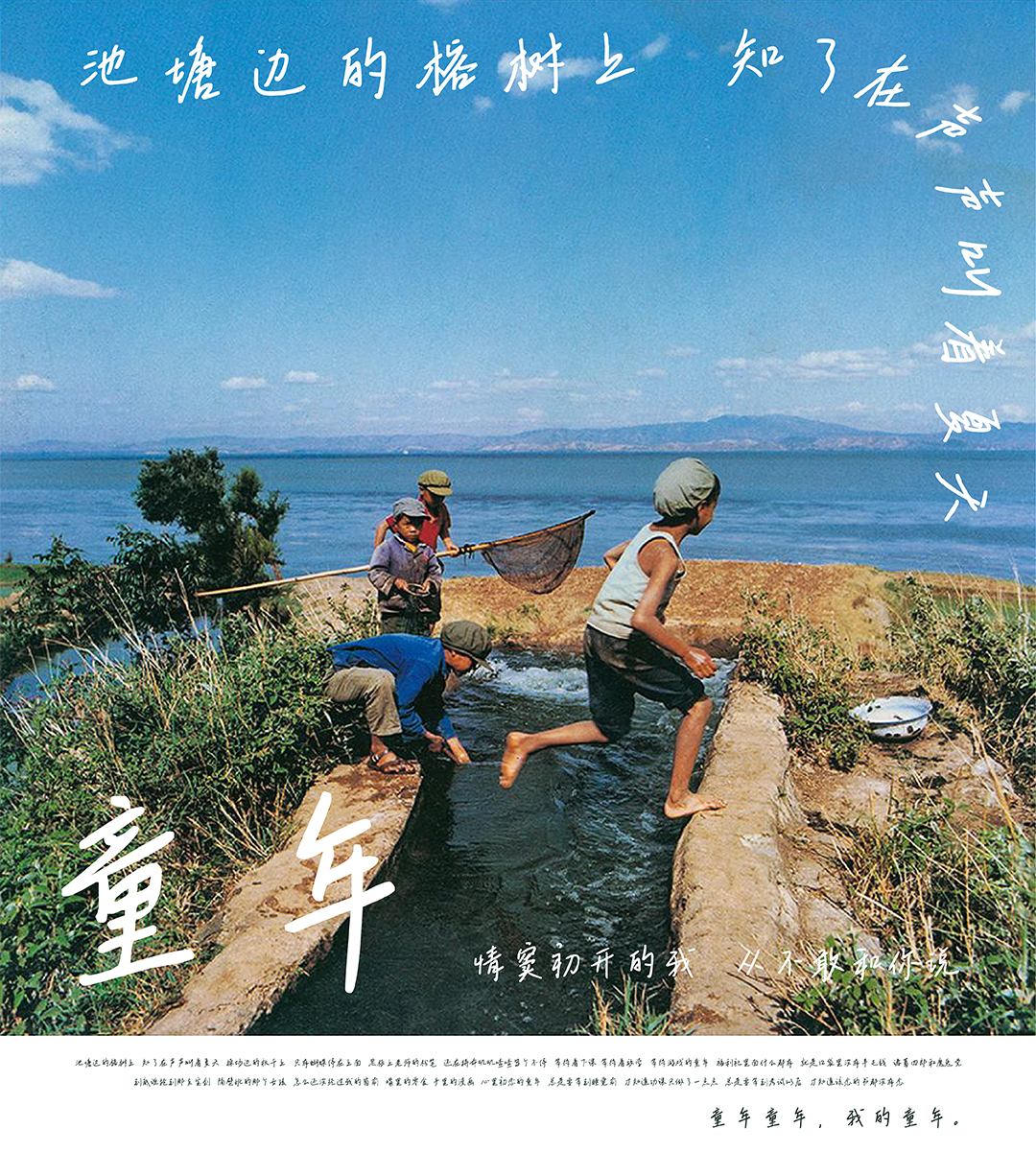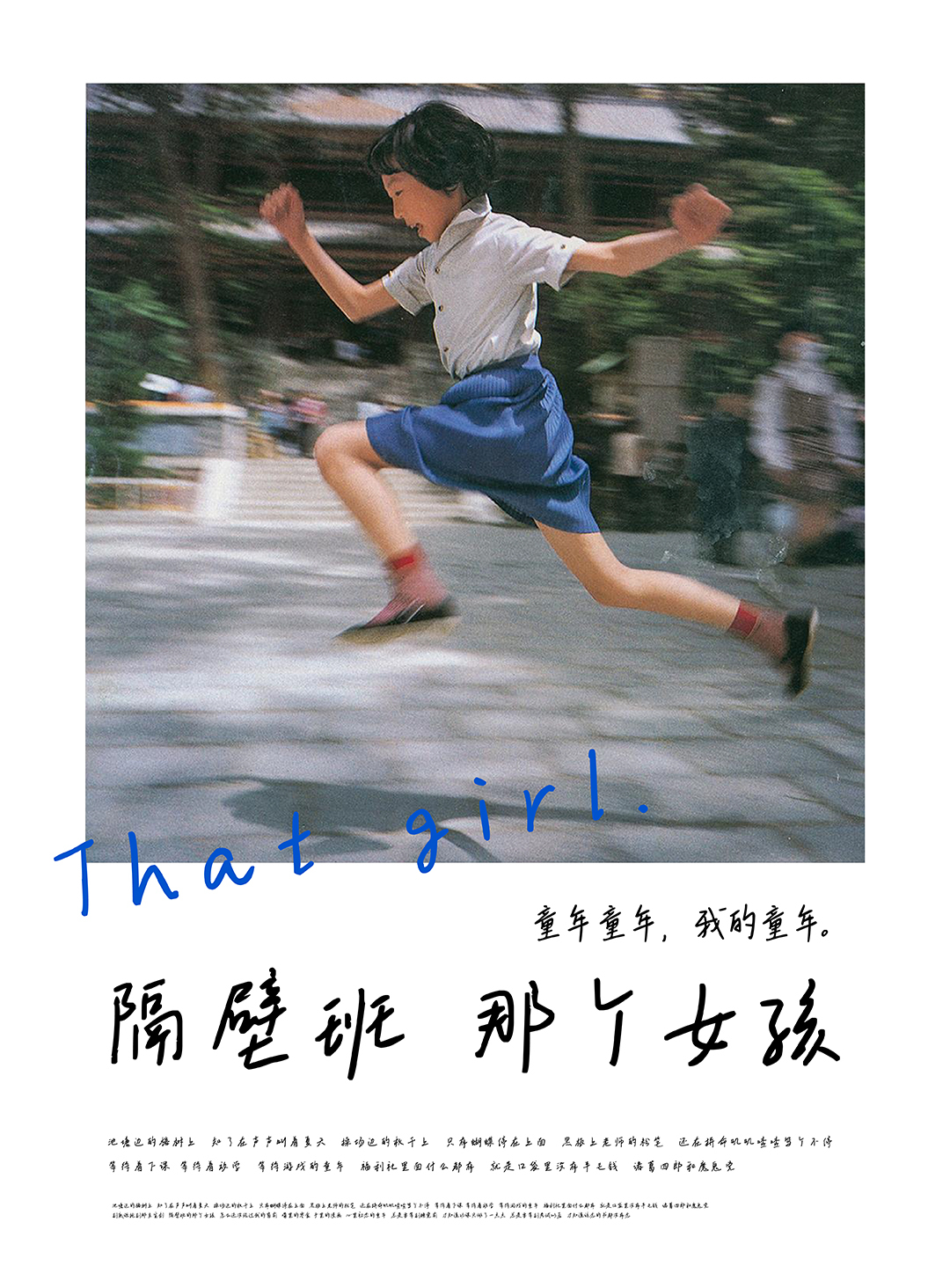
字圈也字绮梦手迹
Cofont-YEqimengGB
字圈也字绮梦手迹的每个字体手迹各不相同,单看一个字迹显得平平无奇,然而精妙之处就在于看似很难找到笔画的共性,但字句成章的时候,整体便散发出慵懒随性的气息,笔画复杂抑或简单的字迹组合在一起,不会让人觉得各自疏离,而是字体间和谐相处,取长补短的快乐感受。
总的来说,绮梦手迹融入了当今审美和自我个性风格的一种字体,具有传统中的新生儿的气质,是年轻人喜欢的一种字体。